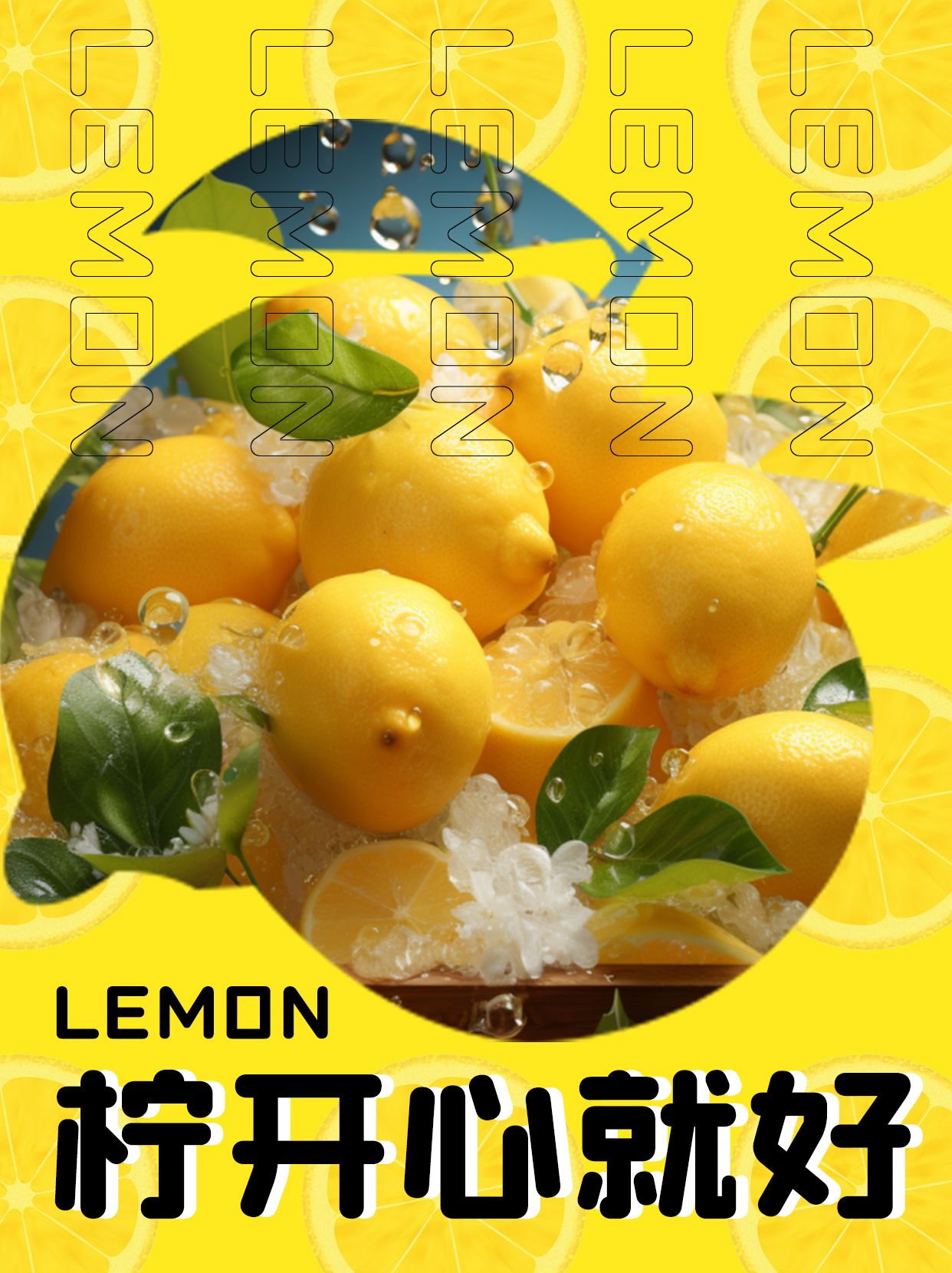
探索视觉盛宴:精选标题字体的魅力之旅
在设计的浩瀚星空中,标题字体犹如璀璨的星辰,引领着观者的视线,赋予作品以灵魂。今天,就让我们一起踏上这场探索之旅,揭秘那些让人过目难忘的标题字体,感受它们独有的魅力与风情。
一、现代简约的时尚感:励字志向黑简 中粗
首先推荐的是励字志向黑简 中粗。它以清晰的线条、简洁的构造著称,如同清晨的第一缕阳光,纯净而明亮。励字志向黑简 中粗不仅易于阅读,还能在瞬间营造出一种高级感,非常适合用于科技、时尚等领域的标题设计,让信息一目了然,直击人心。
二、粗犷豪迈的力量感:造字侠磅礴简繁
首先映入眼帘的是那些粗犷豪迈的标题字体,造字侠磅礴简繁如同荒野中的风,带着不羁与自由。造字侠磅礴简繁线条粗重,结构坚实,能够瞬间抓住人们的注意力,传递出强烈的视觉冲击力。无论是户外广告还是品牌标识,它都能成为焦点,让人难以忘怀。
三、优雅细腻的艺术感:励字造梦简 大粗
与粗犷豪迈形成鲜明对比的是优雅细腻的标题字体。励字造梦简 大粗宛如精致的工艺品,每一个笔画都透露出匠人的用心与才华。励字造梦简 大粗体线条流畅,结构匀称,给人以美的享受。在时尚杂志、高端品牌或艺术展览中,励字造梦简 大粗能够完美融合,提升整体设计的艺术感。
四、个性鲜明的独特性:励字圆梦简 大黑
当然,标题字体的魅力远不止于此。在这个追求个性化的时代,那些具有独特风格的字体更是备受青睐。励字圆梦简 大黑打破了常规的设计规则,创造出前所未有的视觉效果。励字圆梦简 大黑不仅能够彰显品牌的个性与特色,还能激发观者的好奇心与探索欲。
选择一款合适的标题字体,就像是为作品穿上了一件华丽的衣裳。它不仅能够提升整体设计的品质感,还能更好地传达信息、表达情感。希望今天的推荐能够激发你的灵感,让你在设计的道路上不断探索、勇于创新,打造出更多令人惊艳的作品